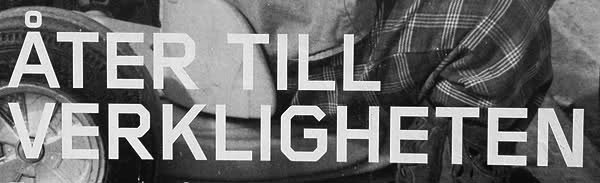
Schrift gesucht, Grotesk
Diese Groteskschrift ist mir jetzt schon einige male begegnet, ich finde sie sehr interessant und würde sie gerne selbst verwenden. Markant ist, dass alle Rundungen eckig abgewinkelt sind. Leider weiss ich nicht wie sie heisst...
Woher stammt denn das Beispiel?
hmm, ja ähnlichkeiten sind da.
Aber I K und G sind schon deutlich verschieden, insofern glaube ich nicht dass es sich um eine Modifikation handelt. Zumal ich die Schrift schon mehrmals gesehen habe, wäre ja ein merkwürdiger Zufall.
Das Beispiel ist aus Stockholm.
Die Schrift habe ich in Deutschland aber auch schon gesehen.
Das Beispiel ist aus Stockholm.
Die Schrift habe ich in Deutschland aber auch schon gesehen.
Ich meinte eher, ob es z.B. einer website entspringt, durch die man draufkommen könnte … oder einen Hinweis auf einen Veranstalter, eine Ausstellung oder was auhc immer. Einfach mehr Infos.
Die Schrift sieht der Gridnik recht ähnlich auch wenn diese ein etwas anderes G hat. Eventuell wurde sie bearbeitet ... :?
ja, das moderna museet verwendet eine individualisierte version der gridnik. nicht ganz identisch, aber dafür frei verkäuflich ist die blender von nik thoenen.
ein bisschen information darüber, wo das herzukommen scheint, gib es hier: http://www.modernamuseet.se/en/Moderna-Museet/About/Moderna-Museets-logo/
Ja das Foto stammt von einem Ausstellungsplakat des Moderna Museets. In dem Link geht es aber um die Logo-Schrift (Handschrift).
Wüstenrot scheint eine ähnliche Schrift in seinen Anzeigen auch zu benutzen, falls das weiterhilft. Auf Anhieb ist mir nur ein anderes großes-i aufgefallen. Bin ich grad durch Zufall drüber gestolpert.
Wüstenrot scheint eine ähnliche Schrift in seinen Anzeigen auch zu benutzen
das ist – wie ich selbst erfragen musste – die unveränderte foundry gridnik, also die vorlage zu der modi?zierten fassung, die das museum verwendet.